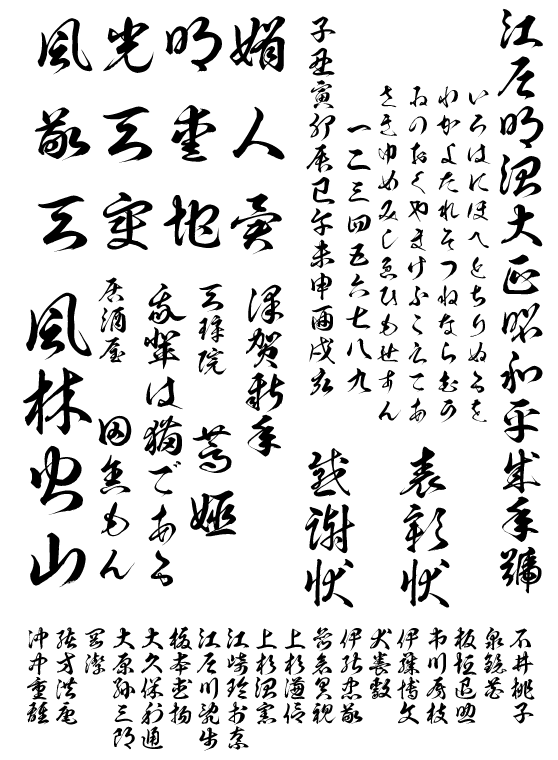
草書体
草龍書体 (KSO草龍)
KsoSouryu
日本古来から伝わる草書体を昭和書体が草龍として復活させました。
約4,179文字(ひらがな83文字、第一水準漢字2965文字、第二水準漢字1131文字)
※カタカナおよび英数字は収録されていません
昭和書体/コーエーサインワークスの紹介
昭和書体は、あらゆる使用目的にマッチする毛筆書体の提供を目指し、揮毫職人が1文字1文字丁寧に書き上げた本格毛筆書体ブランドです。